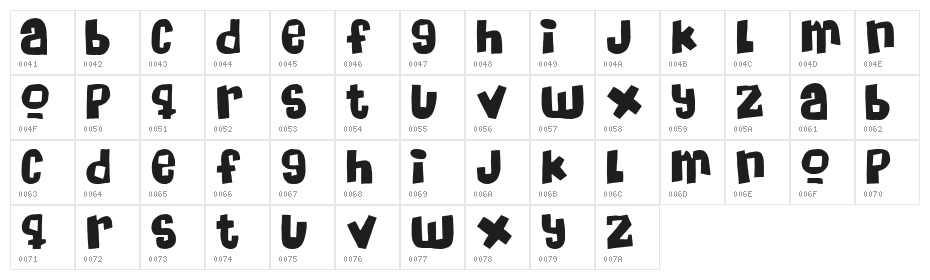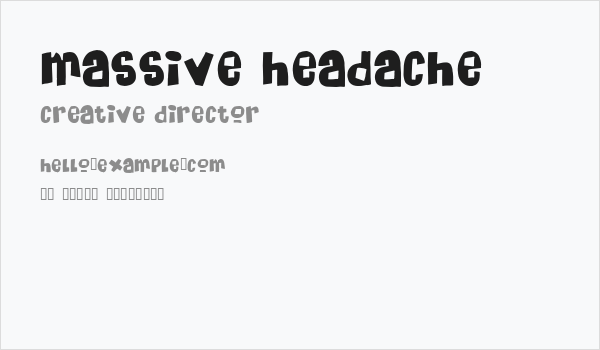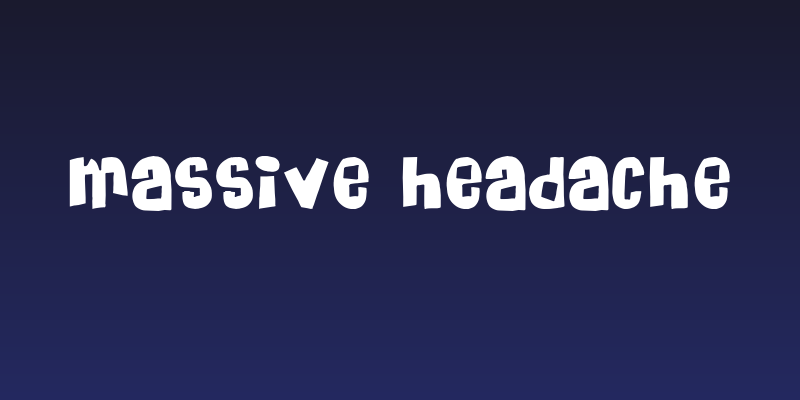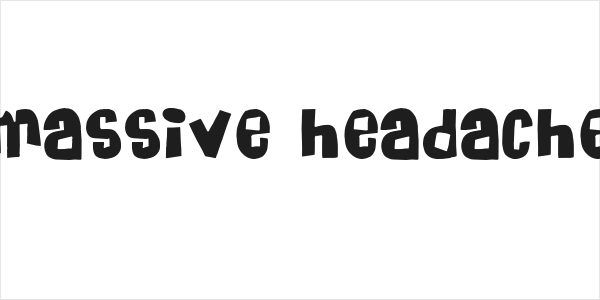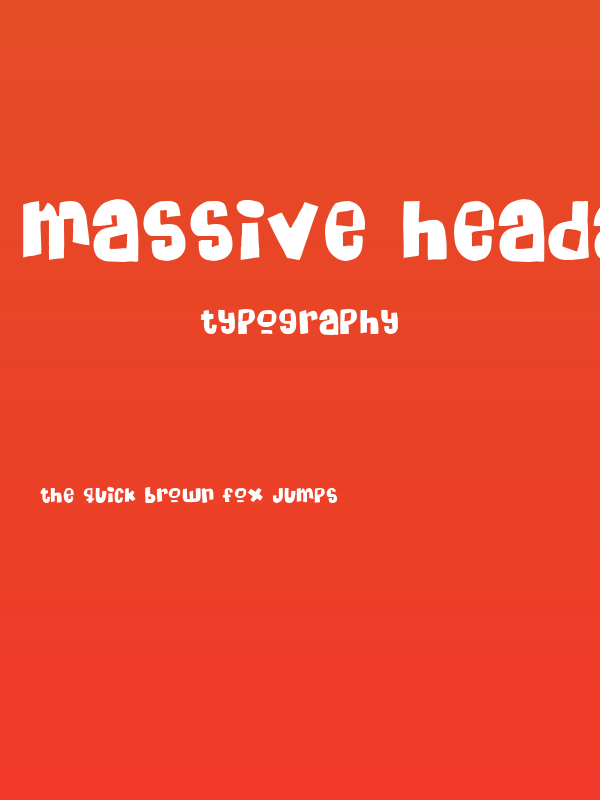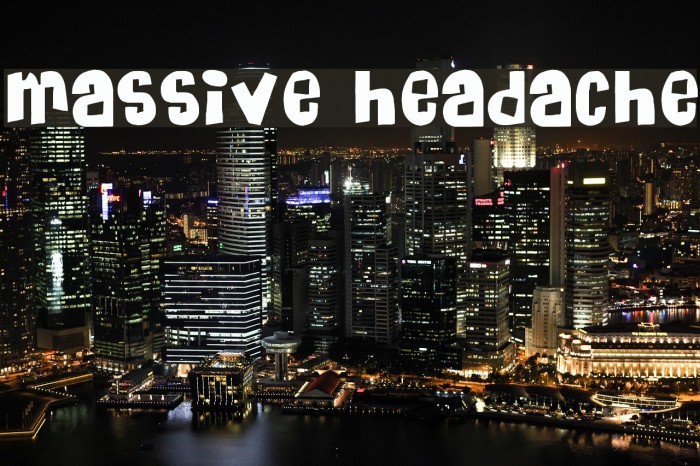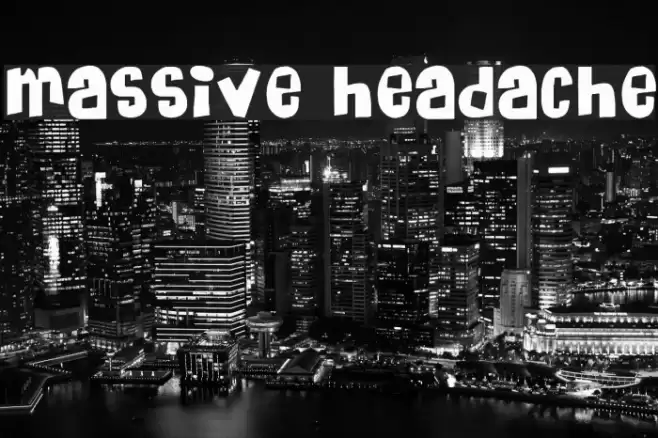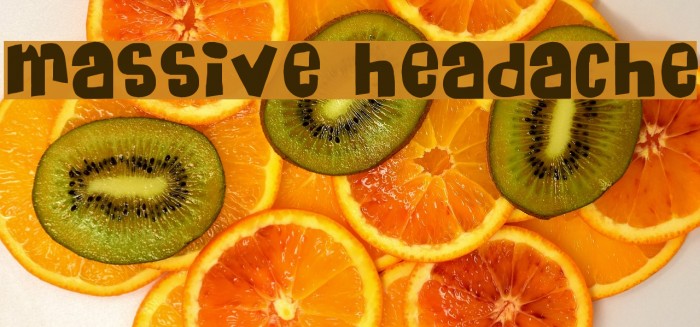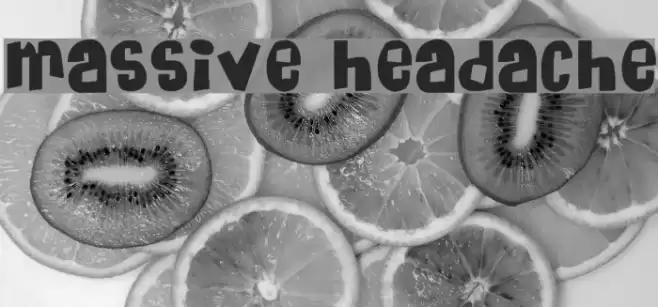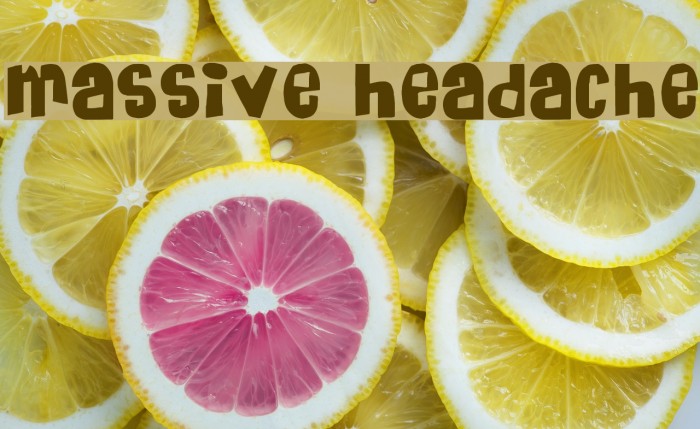
Massive Headache Font
✎ Cartoon
| Categorie | Cartoon |
| Stile generale | Playful, Quirky |
| Caso d'uso | Headlines, Posters, Branding |
| Progetti proposti | Ideal for children's books, comic strips, playful branding, and event posters. |